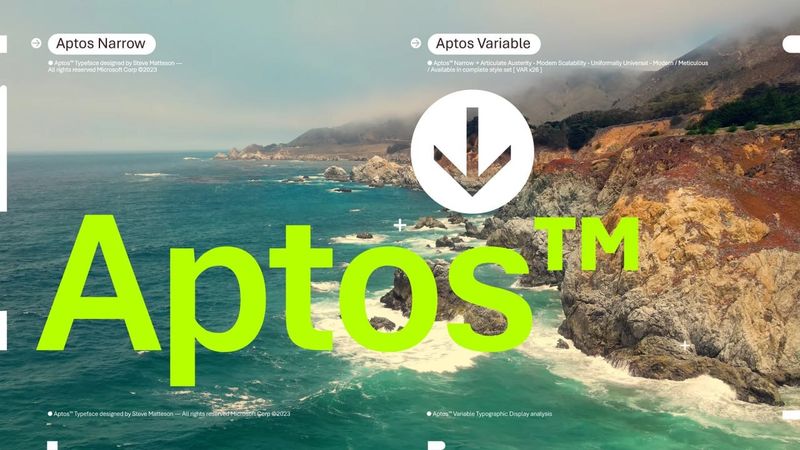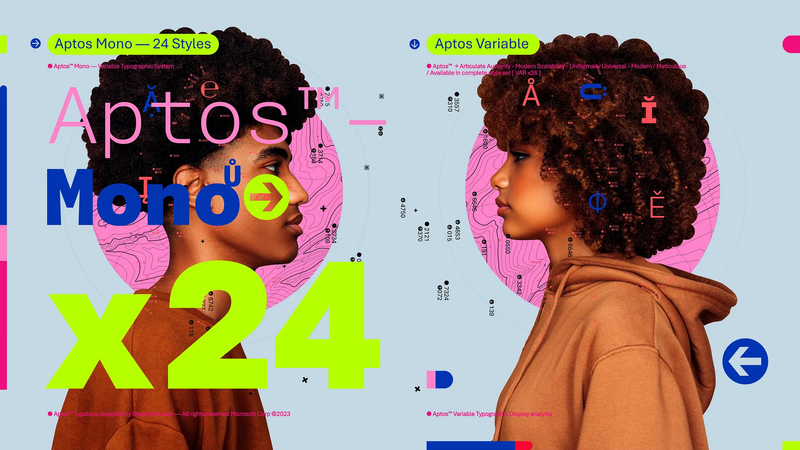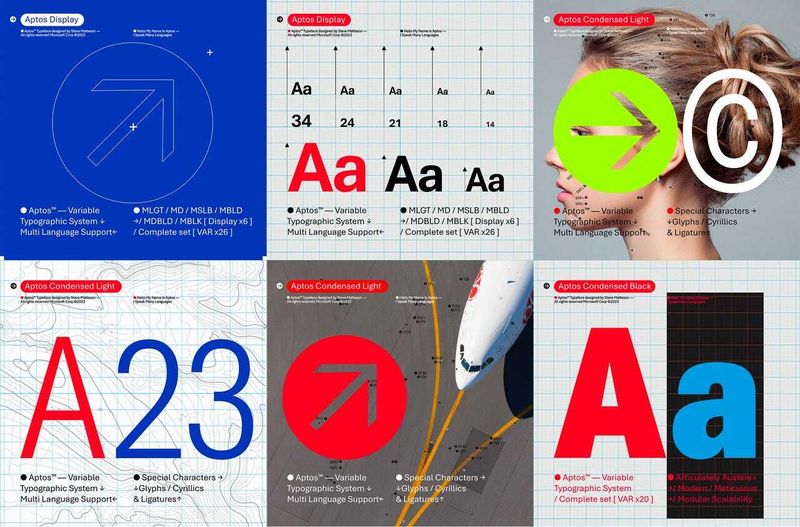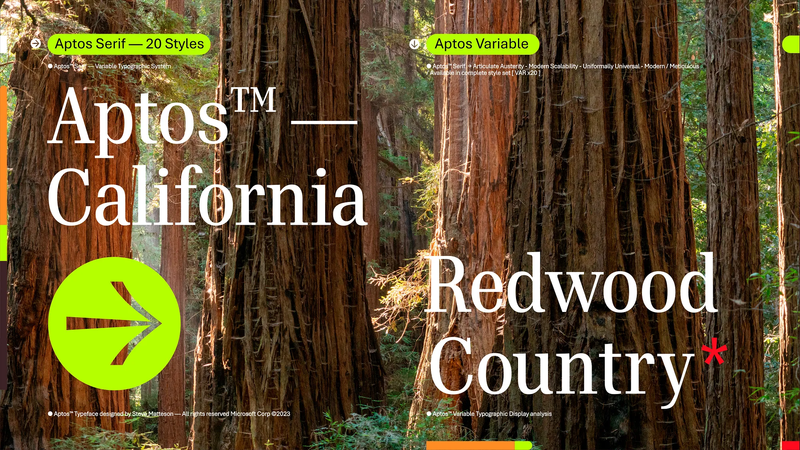
Aptos замість Calibri. У Microsoft показали новий шрифт для всіх офісних програм
Microsoft представила новий шрифт під назвою Aptos, який стане новим шрифтом за замовчуванням у своїх продуктах, таких як Word, Outlook, PowerPoint і Excel. Головний менеджер програм Microsoft, Сай Деніелс, оголосив про це в своєму блозі. Aptos буде використовуватися масштабно та стане основним шрифтом для сотень мільйонів користувачів цих програм. У найближчі місяці компанія планує зробити його шрифтом за замовчуванням для всіх своїх клієнтів.
Aptos font
Протягом останніх 15 років Microsoft використовувала шрифт Calibri за замовчуванням, але з появою екранів високої роздільної здатності, цей шрифт став менш практичним, зауважує Деніелс. Aptos, натомість, має прості форми букв і рівні штрихи, що робить його легкочитабельним. Він не має зарубок і названий на честь міста Aptos в Каліфорнії.
Aptos font microsoft - 1
Aptos font microsoft - 2
Aptos font microsoft - 3